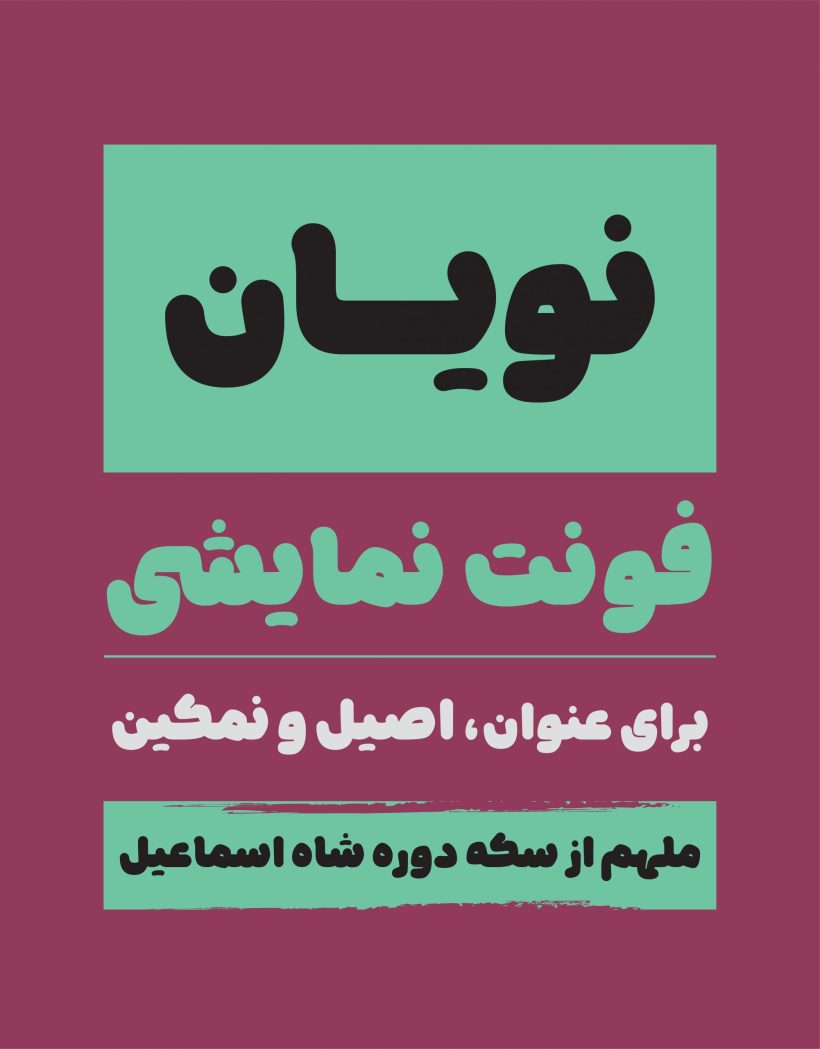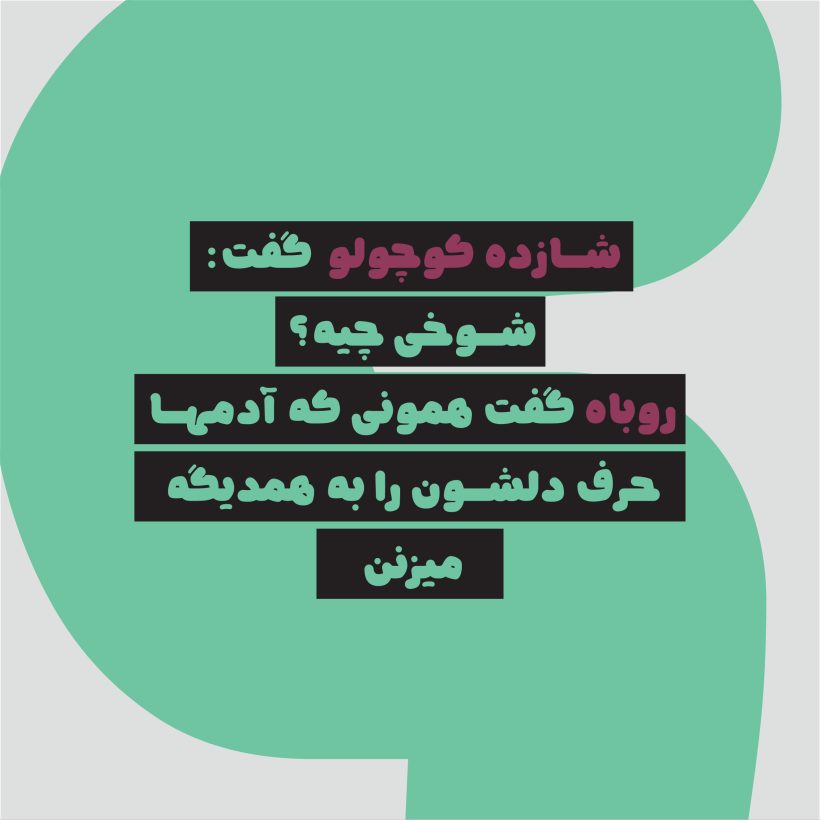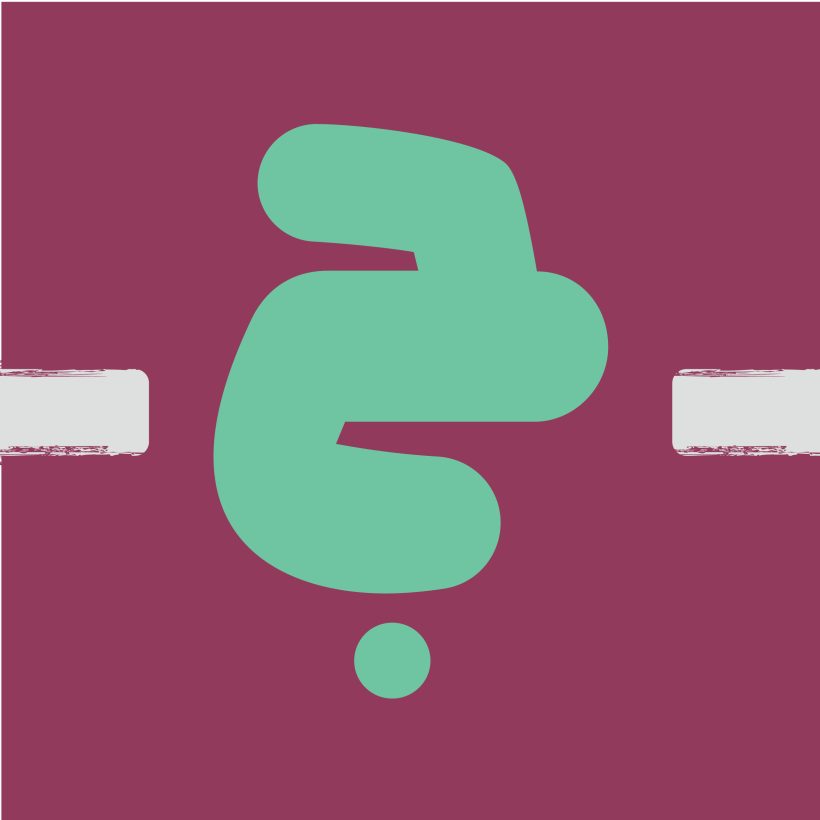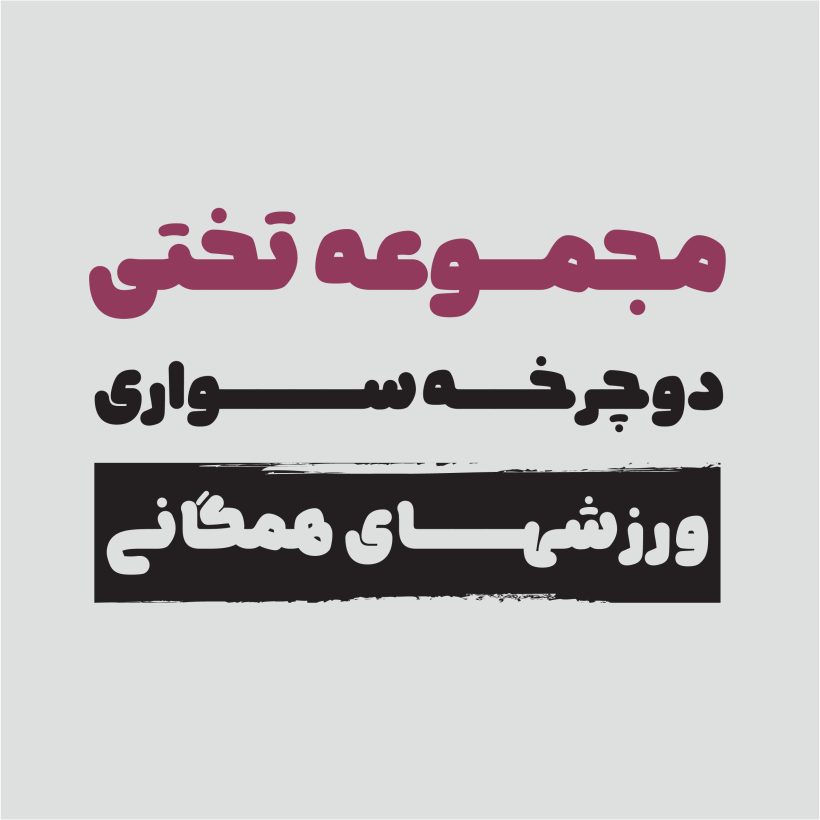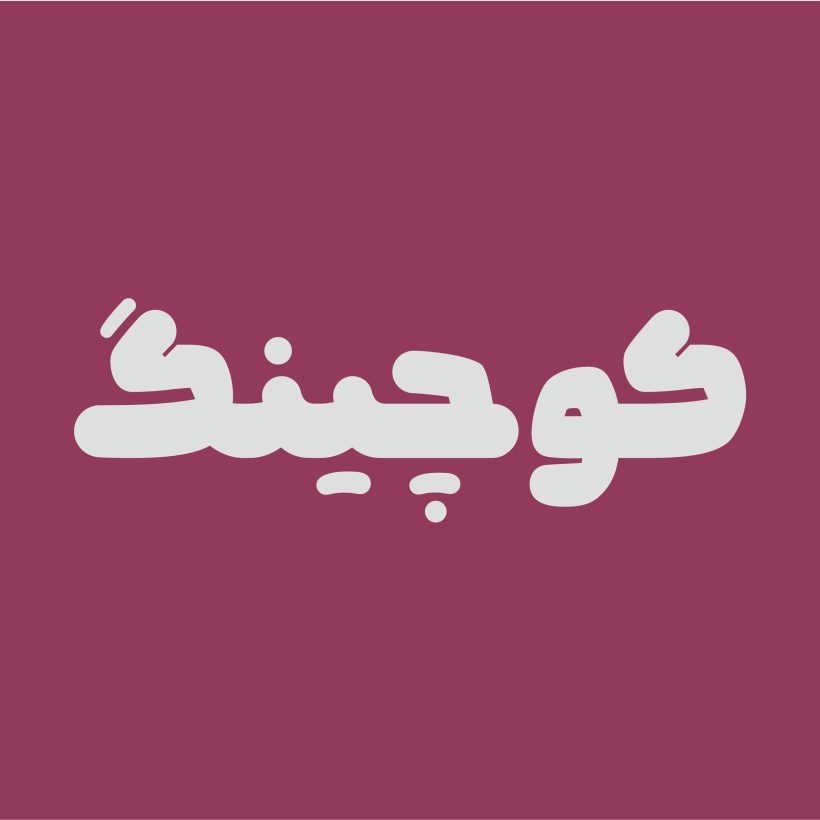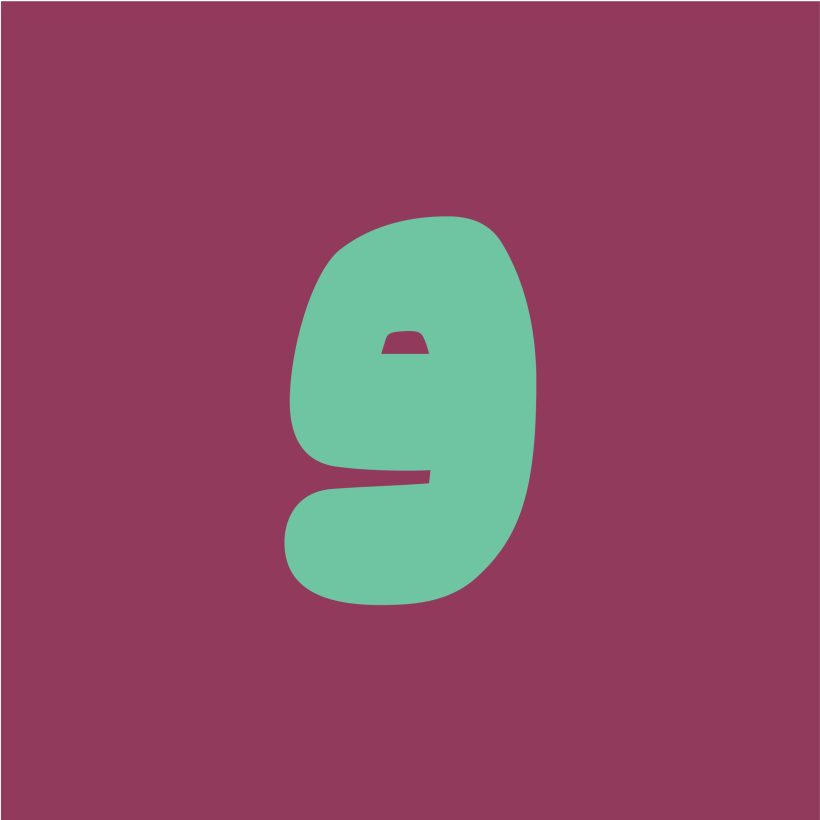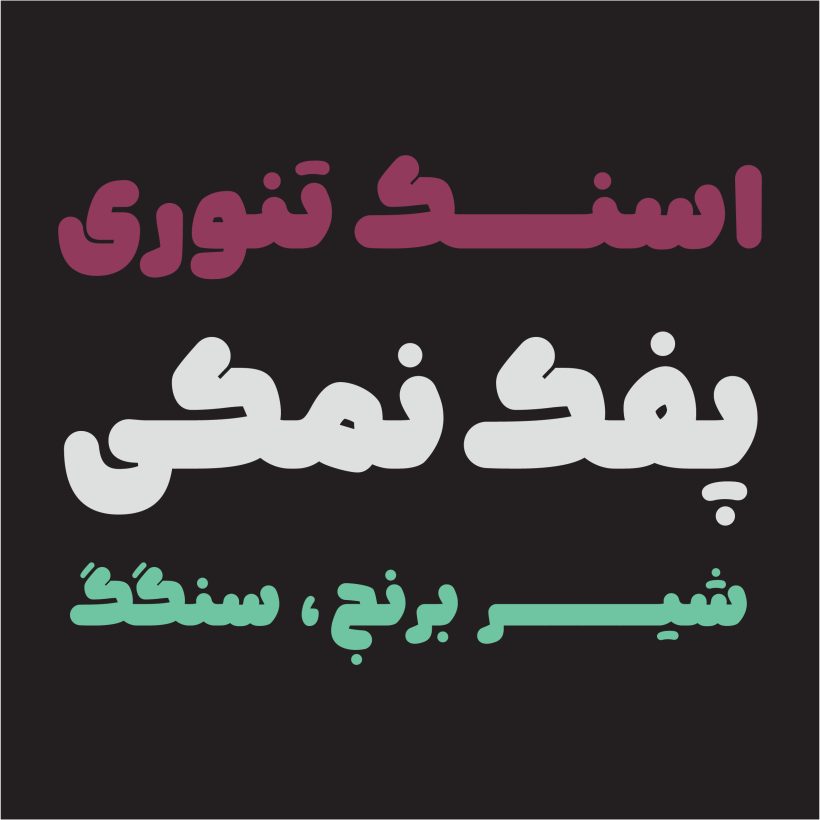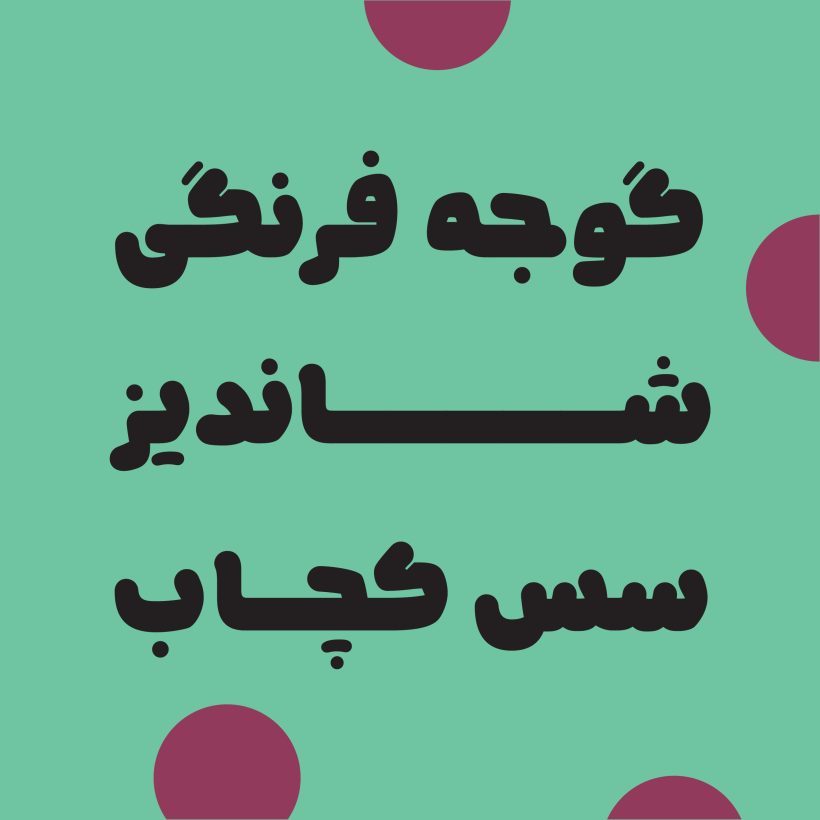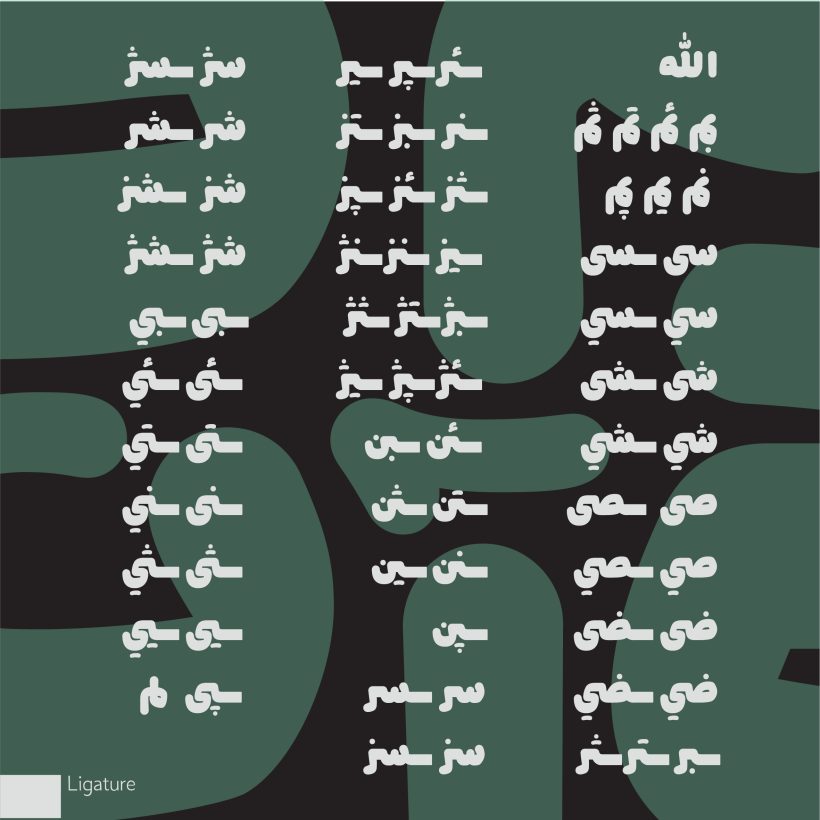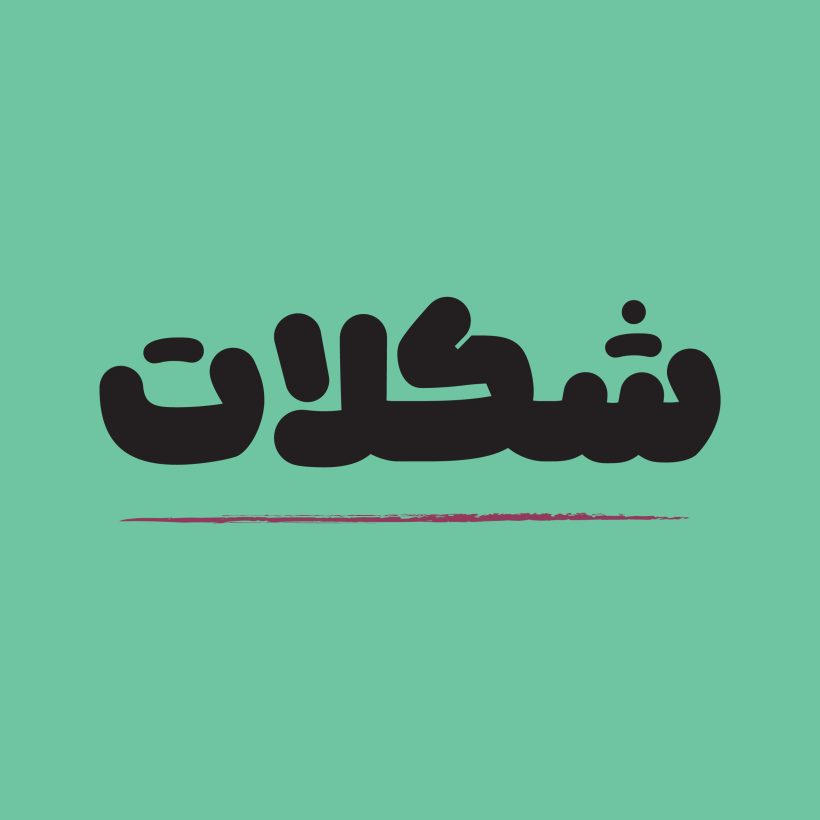
فونت نویان
فونت نویان ملهم از خط سکه شاه اسماعیل اول صفوی(محفوظ در کتابخانه آستان قدس رضوی) است. خط سکه مورد نظر دارای لحنی ساده، بامزه و در عین حال اصیل است و در فونت نویان نیز تلاش شده این ویژگی های تا حد ممکن حفظ شود. نویان، فونت نمایشی و در یک وزن سنگین است و برای عناوین و عبارت های کوتاه کاربرد دارد. زاویه شروع و پایان استروک های فونت نویان با فرم های منحنی طراحی شده است و حرکات توامان استروک های منحنی که با گردش های داخلی زاویه دار همراه شده، لحنی نو و متفاوت را تداعی می کند. نویان در عین سادگی و روانی دارای لحنی شیرین و نمکین، نرم و صمیمانه، بامزه و اصیل و گرم و دوست داشتنی است. نویان برای برندها و موضوعات تجاری به روز، پویا، صمیمانه و مضامین کودکان و نوجوانان مناسب است.
قواعد کرنینگ و اعراب گذاری ها در فونت نویان اعمال شده است. نویان دارای لیگیچر و کارکترهای جایگزین است تا برحسب نیاز و برای زیبایی بیشتر به کار گرفته شود.
اعداد فارسی و عربی در فونت نویان تنظیم شده و قابل استفاده است.
طراح فونت: معصومه مصلح